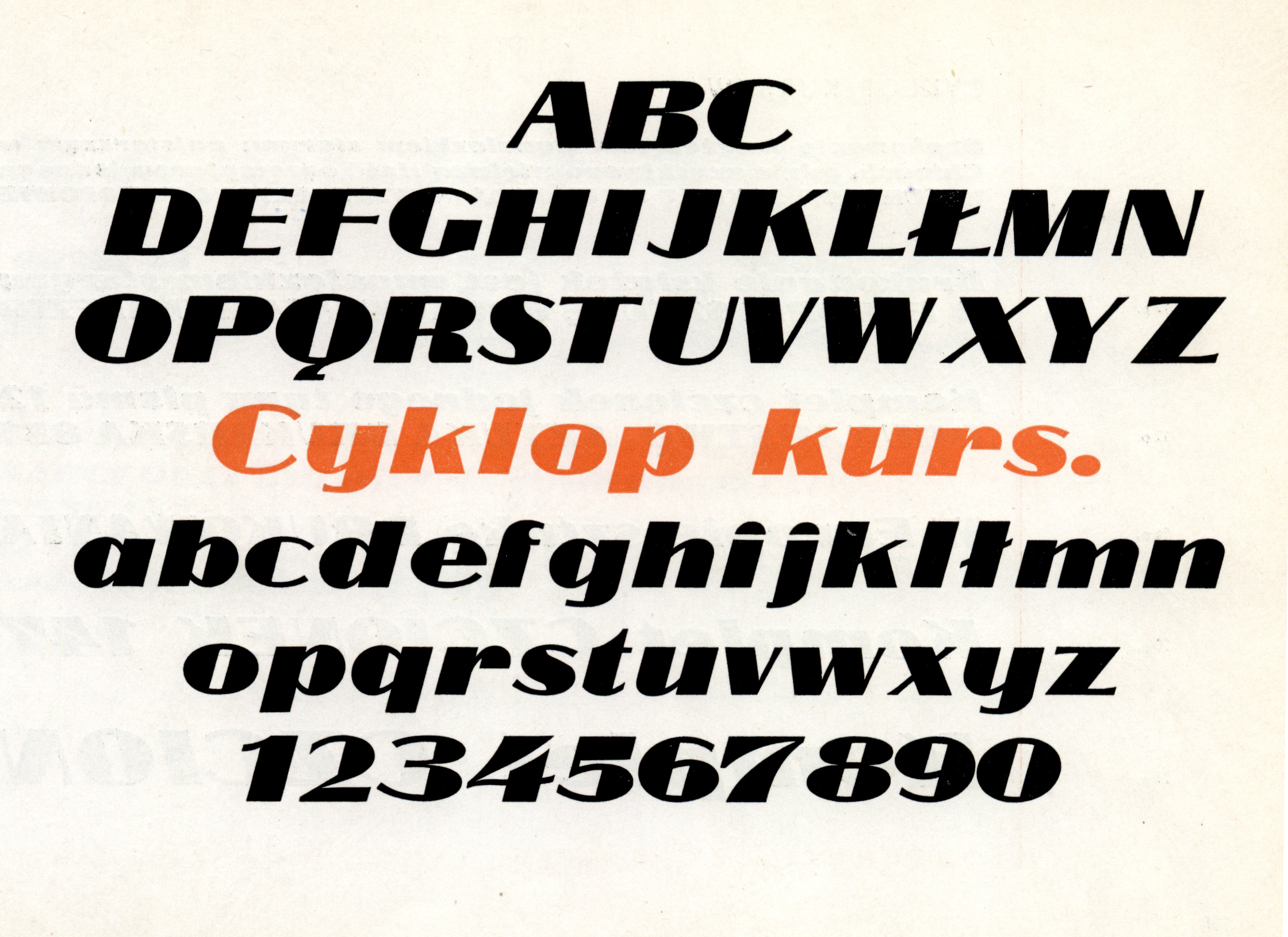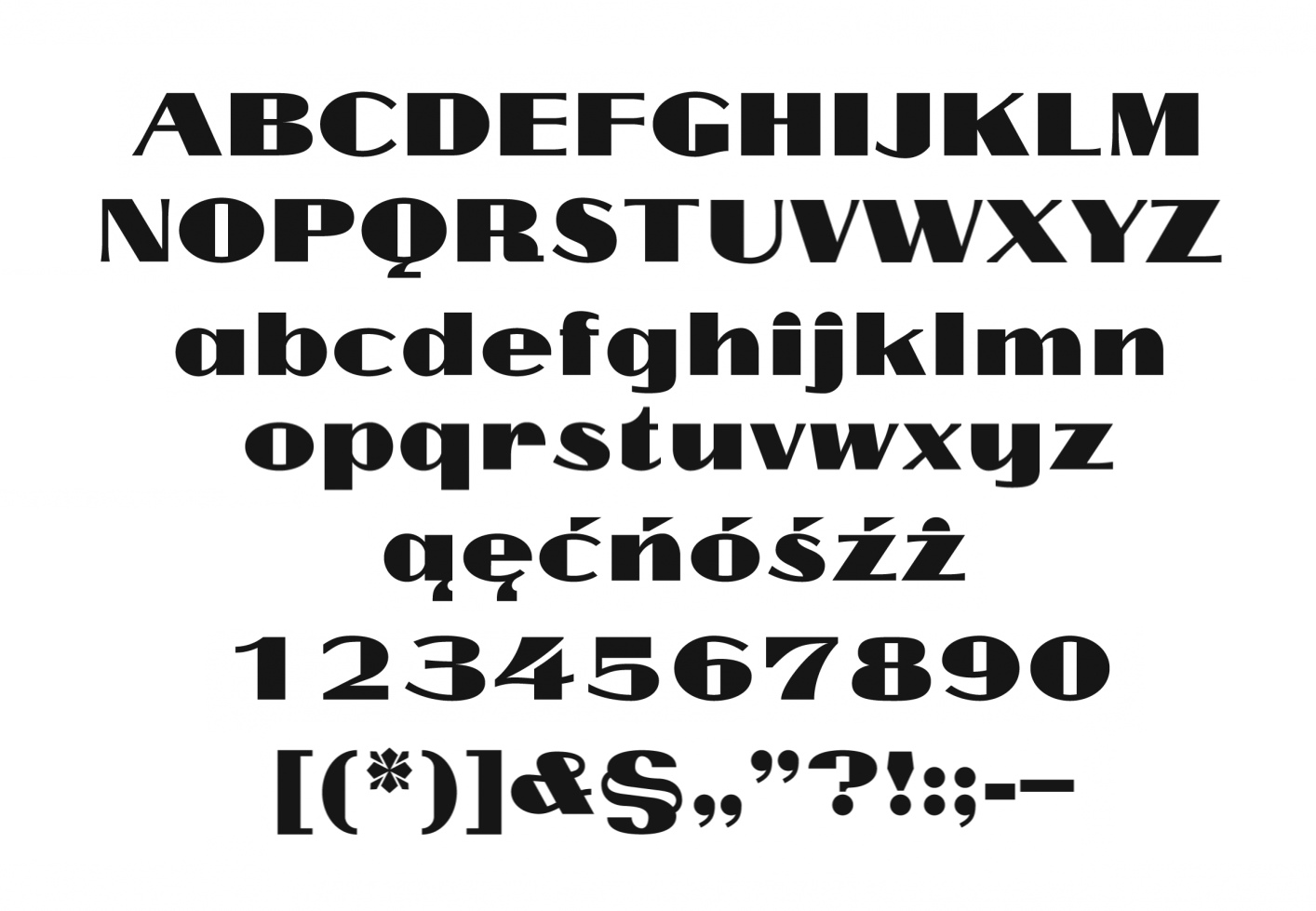
Cyklop
Pismo dwuelementowe, bezszeryfowe, o bardzo dużym skontrastowaniu elementów cienkich i grubych, szerokie w oczku. Charakterystyczne litery: ą, f, j, o, B, D, G, Q – oraz dwie o różnej konstrukcji litery: s, ś, S, Ś. Cyklop można od razu rozróżnić po literze O, podobnej do pinezki. Pismo to ma dwa rodzaje litery w. Cyklop powstał w odlewni Jana Idźkowskiego w Warszawie około 1931 roku.
Istnieją dwie odmiany pisma: Cyklop Kursywa i Cyklop Antykwa.
W 2008 roku digitalizację odmiany pochylonej wykonał Janusz Marian Nowacki, na podstawie odbitek z fabrycznego katalogu Odlewni Czcionek w Warszawie. Wygenerował on także odmianę prostą, na podstawie 11 liter pokazanych w Podstawach techniki wydawniczej (Warszawa 1967). Fonty są do pobrania tutaj.
W 2017 roku digitalizację odmiany prostej i pochylonej wykonali Marcin Dybaś i Joanna Kotas, w oparciu o komplety czcionek z zasobów Muzeum Książki Artystycznej w Łodzi. Fonty z digitalizacją nie zostały opublikowane.